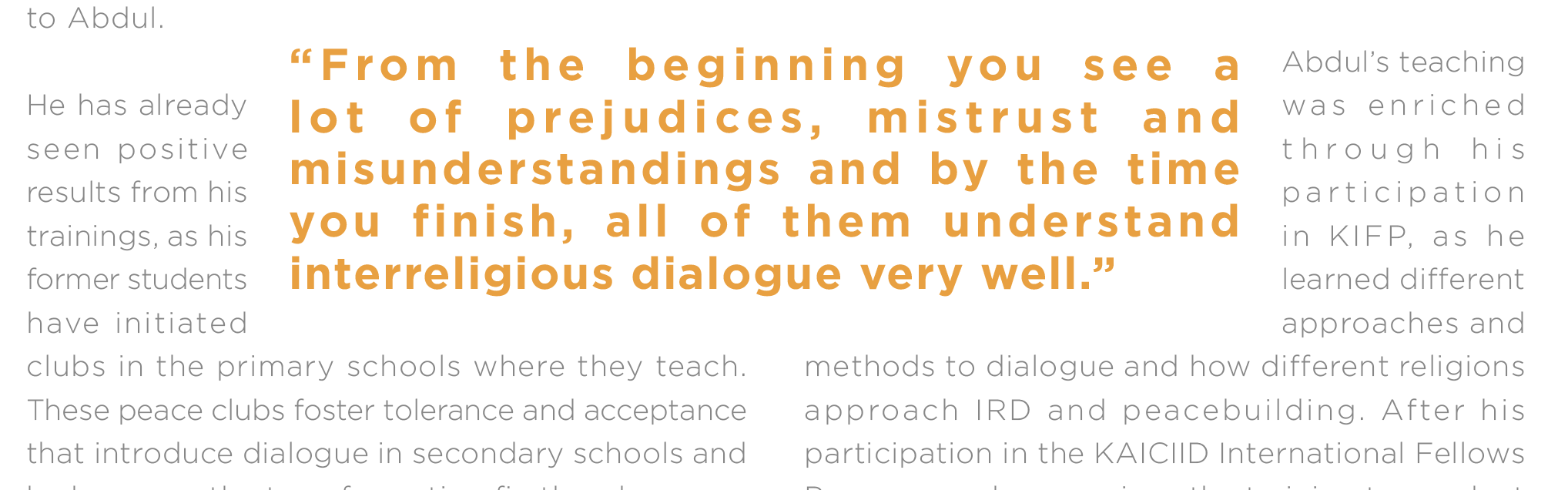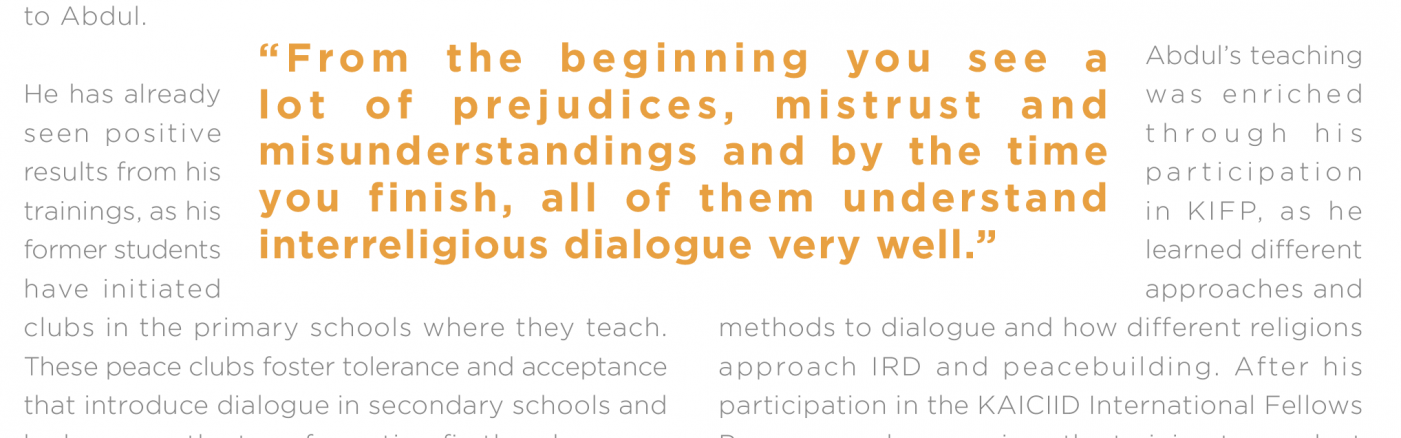
Id-CC_Zeichen-/Wortabstände_Blocksatz
Ich setze gerade eine Publikation und habe mittlerweile echt ein ziemliches Problem, weil der Kunde mit den Wort- und Zeichenabständen nicht zufrieden ist. (Zusatzinfo: Viel Erfahrung habe ich in dem Bereich leider noch nicht!)
Grundsätzlich habe ich mir mal ein Format für den Fließtext angelegt. Beim Punkt "Abstände" bin ich derzeit bei folgenden Werten:
Wortabstand                80/100/110
Zeichenabstand         -10/0/10
Glyphensaklierung   100/100/100
einzelnes Wort:  Blocksatz
Adobe Absatzsetzer
Das riesen Problem ist hier, dass der Kunde Blocksatz und keine Wortabtrennungen möchte und ich somit an manchen Stellen, wie bei den gewünschten Pull-out-quotes, leider zu keinem guten Ergebnis komme. (Auch nicht wenn ich die Breite der Pull-Out-Box ändere, aber das sollte klar sein.)Bildschirmfoto 2016-06-06 um 09.54.48.png
Mit den Voraussetzungen "Blocksatz" und "keine Trennungen" kannst du nur das Layout über den Haufen schmeißen und die Spaltenbreite derart breit machen, dass der Blocksatz sich von allein halbwegs vernünftig ergibt.
Danke, das habe ich fast befürchtet... Das Problem ist zusätzlich, dass der Kunde, nachdem ich ca. 100 Seiten linksbündig (war im Grundlayout so vorgesehen) gesetzt habe, dann umgeschwenkt ist und unbedingt auf Blocksatz umstellen wollte. D.h. dass die Variante, das Layout umzuschmeißen, wohl das Worst-Case-Szenario darstellt..
Diesem Wunsch bin ich auch gerade begegnet: Blocksatz war gewünscht, aber es sollte keine Trennungen geben, weil viele (lange) Namen in dem Text vorkamen. Dann bekommt man entweder riesige Löcher zwischen den Wörtern oder ruiniert die Laufweite der Schrift wie in deinem Beispiel. Ich mache beides nicht, die Lösung war Flattersatz. Blocksatz ohne Trennungen sieht immer übel aus.
Auf Bertels Idee war ich nicht gekommen. Aber das ginge freilich auch, eine enorme Breite der Kolumne. Mit numerierten Zeilen, damit man den Anschluß beim Lesen findet.
Der eingestellte Zeichenabstand ist etwas zu eng für kleine Grade.
Da kann man doch mal froh sein, dass der Text deutsch und nicht finnisch ist, sonst wären die Wörter wohl noch länger. Andererseits wäre es dann dem Kunden vermutlich eher einsichtig, dass er zwei Sachen verlangt, die nicht miteinander vereinbar sind.
Man könnte natürlich alles englisch schreiben, denn da sind die Wörter meistens kürzer als im Deutschen und es geht mit dem Blocksatz ohne Trennung besser auf. Aber nein, Du sagst ja, dass es viele lange Namen sind, da nützt das dann auch nichts.
Was mir noch einfällt: Spiralsatz, da hat man keine Zeilenenden (bis auf eines ganz am Schluss) und daher keine Löcher im Satzbild. Wenn man das dann auf eine Drehscheibe druckt, ist das auch gar nicht mal so furchtbar schlecht lesbar.
Kleinere / schmalere Schrift in den Zitaten wäre auch noch eine Not(!)lösung.
Letztlich kann man nicht ein Ergebnis verlangen, und dabei alle Werkzeuge ausschließen, die das Ergebnis ermöglichen würden: Blocksatz erfordert Trennungen oder sehr einfache, breite Layouts – wenn beides nicht erlaubt ist, gibt es gestreckte Wörter oder Löcher. Das hat nichts mit gestalterischer Fähigkeit oder Unfähigkeit zu tun, sondern mit Statistik und Verteilungsmathematik.
Pragmatische Lösung: Trennungen doch erlauben, aber sehr gezielt trennen – Trennung kann man gut oder schlecht machen, vielleicht gibt es nur eine Aversion gegen schlechte Trennungen.
Blocksatz mittels Austreiben durch Zeichenabstände, wie im Beispiel, find ich eigentlich noch scheußlicher als zu grosse oder zu enge Wortabstände. Vielleicht den Zeichenabstand mal auf Null setzen und vorsichtig hier und da trennen und das Ergebnis mal zum Vergleich vorlegen …
Die normal laufende Gotham finde ich für Fließtexte schwierig. Nimm lieber die Narrow-Version (ich glaube selbst von Hoefler wird sie dafür empfohlen). Das dürfte, wie Sebastian schon anklingen ließ, für Abhilfe sorgen. :-)
Und die Zitatbreite lässt die umlaufende Textspalte so eng werden – das kann nur in die Hose gehen. Da wirst Du wohl ohnehin noch mal nachjustieren müssen.;-)
VIelen Dank für eure Hilfe, dachte schon ich durchschau das einfach nicht. Hilft mit auch etwas beim Kunden zu argumentieren.
Ich werd mir das wirklich mal mit der Narrow Version anschauen, guter Tip Robert!
Bzgl. der Abtrennungen:
Mir bleibt sowieso nichts Anderes übrig als gezielt und sehr sparsam zu trennen, da das Austreiben durch Zeichenabstände, wie Hans das schon bemerkt hat, wirklich furchtbar ist und ein absolut inakzeptables Ergenis liefert. Ich muss da wohl noch ein wenig tüfteln (mit Allem, das mir zur Verfügung steht.. was ja anscheinend nicht mehr viel ist.)
Tja, da hattes es Gutenberg ja tatsächlich leichter als wir, als er die Bibel in Latein setzte, denn zum einen hatten die von ihm verwendeten Lettern einen guten Vorrat an unterschiedlich breiten Alternativ-Glyphen, sowie ein Sortiment an Abkürzungszeichen und Ligaturen, mit denen man so einiges an Platz aus der Zeile herausschinden konnte. Die Leser waren das dann auch noch von den ja auch auf Ökonomie beim Schreiben bedachten Handschriften gewohnt, solche Abkürzungen für lateinische Endsilben immer wieder anzutreffen. Das alles machte einen Blocksatz ja schon leicher.